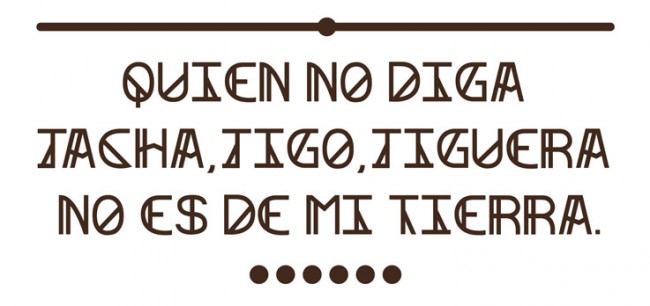
Tipografías gratuitas: Footter Font ha sido diseñada por David Serrano para la revista Neo2. Esta tipografía no se puede vender o regalar a terceros. El uso comercial de esta tipografía deberá incluir el siguiente texto legal: “La tipografía Footter Font ha sido diseñada por David Serrano para la revista Neo2”.
Una tipografía experimental caracterizada por la geometría y los diversos trazos rectos que atraviesan cada caracter y glifo.
Footter Font Typography Designed by David Serrano for Neo2 magazine. This typeface can’t be sold or given to anybody. The commercial use of this typography should always incluye: “Footter Font typography Designed by David Serrano for Neo2 magazine”.
An experimental typeface characterized by geometry and the various straight strokes that traverse each character and glyph.